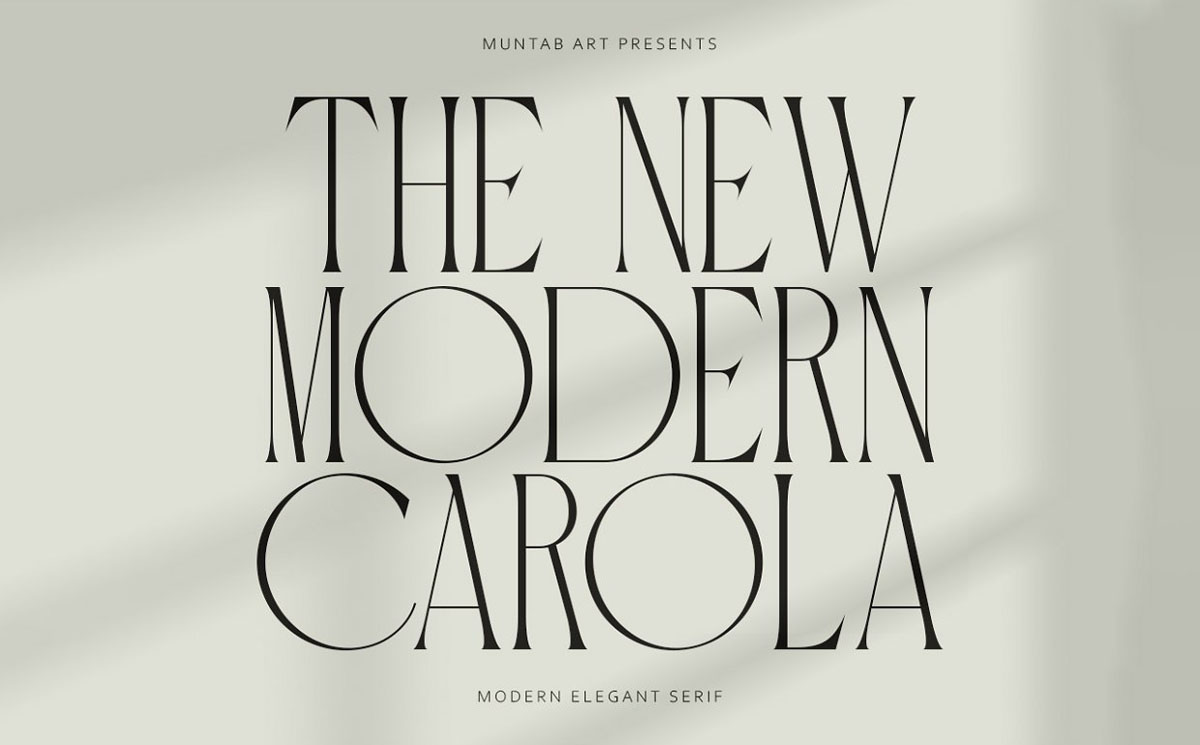
Font chữ thời trang sang trọng chân sang trọng SVN Carola | Phông chữ Việt hóa miễn phí
Font chữ thời trang sang trọng SVN Carola là lựa chọn hoàn hảo dành cho các nhà thiết kế đang tìm kiếm sự tinh tế, đẳng cấp và quyến rũ cho dự án đồ họa của mình. Với đường nét chân chữ (serif) được gọt giũa tỉ mỉ mang phong cách cổ điển kết hợp với nghệ thuật hiện đại, phông chữ này giúp nâng tầm giá trị thương hiệu và tạo ấn tượng thị giác vô cùng mạnh mẽ. Bài viết dưới đây sẽ giúp bạn khám phá chi tiết toàn bộ vẻ đẹp, chức năng nổi bật và ứng dụng thực tế của bộ phông chữ Việt hóa miễn phí tuyệt vời này.
Font Chữ Thời Trang Sang Trọng SVN Carola | Phông Chữ Việt Hóa Miễn Phí Cho Thiết Kế Đẳng Cấp
Trong ngành thiết kế đồ họa cao cấp, lựa chọn kiểu chữ phù hợp không chỉ đơn thuần là truyền tải nội dung văn bản mà còn là chìa khóa vàng để định hình phong cách và tạo dựng cảm xúc cho thương hiệu. SVN Carola nổi lên như một điểm sáng rực rỡ trong dòng phông chữ Serif thời trang, mang đến sự giao thoa hoàn hảo giữa vẻ đẹp quý phái kiểu Âu Mỹ và sự trang nhã đương đại. Từng nét chữ được tạo hình cẩn trọng với sự cân bằng tuyệt đối giữa yếu tố nghệ thuật và tính ứng dụng thực tiễn.
Đặc biệt, bản SVN Carola đã được việt hóa hoàn chỉnh, hỗ trợ đầy đủ các dấu thanh tiếng Việt một cách chuẩn xác và mượt mà. Điều này giúp các nhà thiết kế Việt Nam dễ dàng sáng tạo nên những tác phẩm đồ họa mang đậm nét sang trọng quốc tế mà không gặp bất kỳ rào cản nào về mặt ngôn ngữ hay lỗi hiển thị ký tự.
1. Đường Nét Serif Thời Trang Sang Trọng Và Đầy Tinh Tế
Chức năng nổi bật đầu tiên của SVN Carola chính là cấu trúc đường chân (serif) được tạo hình vô cùng sắc nét và quý phái. Sự tương phản rõ rệt giữa các nét thanh mong mong và nét đậm chắc chắn mang lại hiệu ứng thị giác đỉnh cao, đậm chất truyền thông thời trang cao cấp. Kiểu dáng này cực kỳ phù hợp với các thương hiệu xa xỉ như nước hoa, trang sức, thời trang haute couture hay các dịch vụ cao cấp muốn khẳng định vị thế dẫn đầu.
2. Bản Việt Hóa SVN Carola Chuẩn Xác, Tối Ưu Cho Tiếng Việt
Một tính năng quan trọng khiến bộ font này trở thành sự lựa chọn hàng đầu của giới thiết kế trong nước là chất lượng Việt hóa đạt tiêu chuẩn chuyên nghiệp. Tất cả các ký tự có dấu như ê, ơ, ư cùng hệ thống các dấu thanh (sắc, huyền, hỏi, ngã, nặng) đều được tinh chỉnh khoảng cách, tỷ lệ và độ cao hoàn hảo. Nhờ đó, tổng thể câu chữ tiếng Việt khi trình bày luôn giữ được độ thẩm mỹ nguyên bản của phông chữ gốc, không bị lệch nét hay thô kệch.
3. Hệ Thống Glyphs Và Ligatures Phong Phú Cho Thiết Kế Sáng Tạo
SVN Carola mang đến một thư viện ký tự thay thế (Alternate Glyphs) và bộ nối chữ (Ligatures) đa dạng. Chức năng này cho phép các designer linh hoạt biến tấu các chữ cái thông thường thành những đường uốn lượn nghệ thuật đầy phá cách. Bạn có thể dễ dàng tạo ra những mẫu logo độc bản, các tiêu đề bìa tạp chí ấn tượng hoặc nhãn mác sản phẩm cao cấp chỉ bằng cách thay đổi các ký tự đặc biệt trong phần mềm thiết kế.
4. Khả Năng Hiển Thị Sắc Nét Trên Mọi Nền Tảng Và Định Dạng
Được xây dựng trên nền tảng vector chuẩn xác, font chữ SVN Carola đảm bảo khả năng hiển thị hoàn hảo ở mọi kích thước. Dù được sử dụng trên các ấn phẩm in ấn kích thước lớn như banner, pano, poster sự kiện hay áp dụng trên các giao diện kỹ thuật số như website, banner quảng cáo Facebook, Instagram, phông chữ vẫn duy trì độ nét cao, không bị vỡ hay mờ nét, mang lại trải nghiệm thị giác ấn tượng cho người xem.
SVN Carola được chia sẻ hoàn toàn miễn phí cho mục đích sử dụng cá nhân, giúp các nhà thiết kế trẻ, sinh viên và các agency dễ dàng tiếp cận nguồn tài nguyên chất lượng cao. Bộ font có định dạng chuẩn (OTF/TTF), hoàn toàn tương thích và hoạt động ổn định trên cả hai hệ điều hành phổ biến là Windows và macOS, cũng như tương thích tốt với hệ sinh thái phần mềm Adobe (Photoshop, Illustrator, InDesign) và Microsoft Office.
Những Ứng Dụng Nổi Bật Của Phông Chữ Việt Hóa SVN Carola Trong Thực Tế
Nhờ sở hữu phong cách thời trang sang trọng cùng tính linh hoạt cao, phông chữ Việt hóa SVN Carola mở ra khả năng ứng dụng đa dạng trong nhiều lĩnh vực sáng tạo khác nhau:
• Bộ nhận diện thương hiệu (Brand Identity): Thích hợp làm phông chữ chính cho logo, slogan, tagline của các thương hiệu mỹ phẩm, spa, thẩm mỹ viện, thời trang nữ và các sản phẩm cao cấp.
• Thiết kế bìa tạp chí & Ấn phẩm truyền thông: Nét chữ kiêu sa của SVN Carola là lựa chọn số một cho các tiêu đề trang bìa (Magazine Cover), bài viết thời trang (Editorial Layout) và các catalogue giới thiệu bộ sưu tập mới.
• Bao bì sản phẩm xa xỉ: Giúp các thiết kế vỏ hộp quà tặng, nhãn chai rượu vang, chai nước hoa hay hộp đựng trang sức nâng tầm giá trị thương hiệu trong mắt khách hàng.
• Thiệp cưới & Thiệp mời sự kiện cao cấp: Sự kết hợp giữa nét cổ điển và sự tinh tế tạo nên không gian lãng mạn, trang trọng cho các mẫu thiệp mời dạ tiệc, thiệp cưới sang trọng.